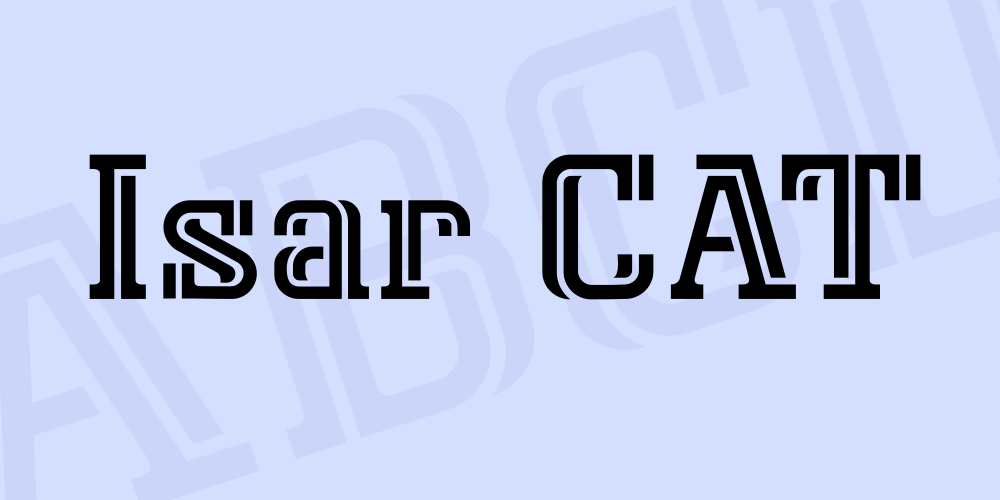
Isar CAT é uma elegante serifada slab-font, perfeita para criar ambientes amigáveis e envolventes que combinam modernidade com simplicidade cuidadosa. Desenvolvida por Peter Wiegel, esta fonte tem um toque de calma que pode transformar qualquer projeto em algo agradável ao olhar. Com sua tipografia clean e sóbria, Isar CAT consegue entrelaçar ideias complexas com uma leitura agradável e confortável para o olho humano. Ideal para aplicações como websites, editoriais de publicações ou até mesmo em material gráfico para lojas físicas que buscam um equilíbrio perfeito entre modernidade e calma. Para quem está à procura de uma fonte que traga tanto estilo quanto conforto visual, Isar CAT é definitivamente a escolha certa. Peter Wiegel criou uma fonte gratuita chamada Isar CAT, disponível através do site http://www.peter-wiegel.de. Esta fonte não só oferece um design único e moderno, mas também traz uma dose necessária de conforto visual que assegura um grande impacto no projeto final. É perfeito para designers que buscam complementos de fontes que não apenas agradam aos olhos, mas também auxiliam na criação de ambientes de design envolventes e relaxantes.